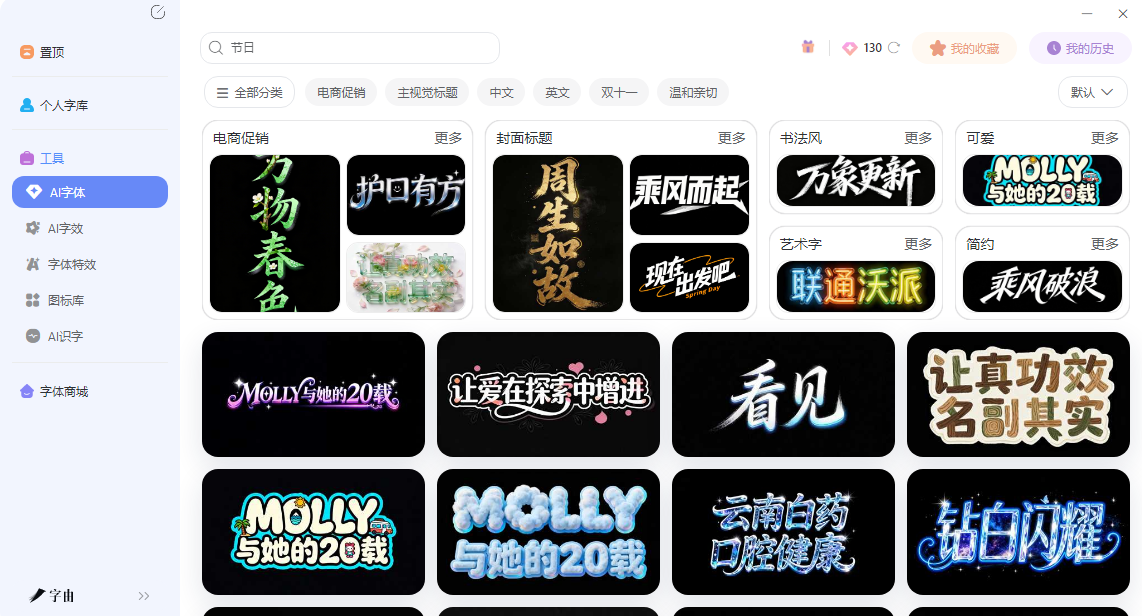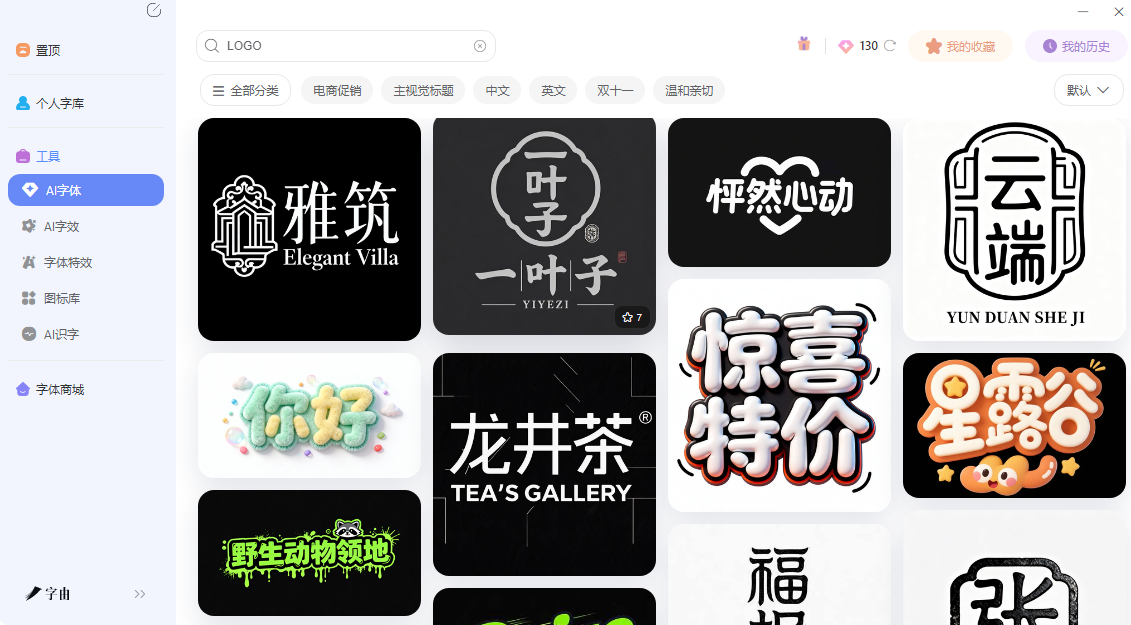
还在用普通字体?试试特殊字体生成器,一键生成
还在羡慕别人轻轻松松就能够拥有特殊字体?现在只需要通过特殊字体生成器就能够轻松实现,不需要你会PS也不需要你会设计,零基础的小白也完全可以上手,今天我就来给大家介绍5个特殊字体生成器,让你不再羡慕别人,可以自己自由地实现设计各种字体,或者不同效果的字体,心动的话先收藏本篇文章码住吧!
字由除了是字体库以外, 它的“AI 字体”功能可以看作一个强大的特殊字体生成器。打开客户端,左侧找到“工具” → “AI 字体”,你会发现里面藏着大量特殊风格的模板。和常规字体库不同,AI 字体生成的不是可编辑文字,而是直接出艺术字图片。你输入自己的文案,选一个模板,点击生成,下载 PNG 就能用。接下来我会教大家如何使用字由的AI字体来生成出特殊字体。
第二步:选择风格分类。在模板区域上方,有场景分类栏。如果你想做故障效果,可以找“科幻/科技感”分类;想做霓虹标题,找“电商促销”或“主视觉标题”分类;想做哥特字,找“文字 LOGO”或直接搜风格标签。
第三步:输入你的文案。点击任意一个模板,进入编辑界面。把默认文字删掉,输入你自己的内容。比如要做游戏封面,输入“FINAL BOSS”;要做海报,输入“限时五折”。
第四步:下载,点击生成,等待6-7秒即可生成图片。生成后,你可以直接下载透明背景的PNG图片,拖放到海报或PPT中使用都是可以的。
其中AI模板我重点推荐的有:
- 故障/Glitch:文字带错位、色差、撕裂感,适合赛博朋克风格、游戏海报。
- 霓虹发光:文字像霓虹灯管,外发光和渐变效果,适合夜间主题、酒吧海报。
- 液态/熔融:文字边缘像融化流动,带扭曲感,适合潮流品牌、实验性设计。
- 3D立体:文字带有厚度和光影层次,适合促销banner、电商标题。
- 材质纹理:文字填充金属、大理石、毛绒等材质效果。
- 哥特/暗黑:文字带尖锐装饰角,中世纪风格,适合万圣节、金属乐队主题。
AI模型预先学习了海量特定风格,比如“赛博朋克”“水墨书法”“卡通泡泡”等。当你选择一个模板并输入文字时,AI不是从零创造,而是把你的文字“装扮”成已学风格的形态,这保证了输出的高度稳定性。
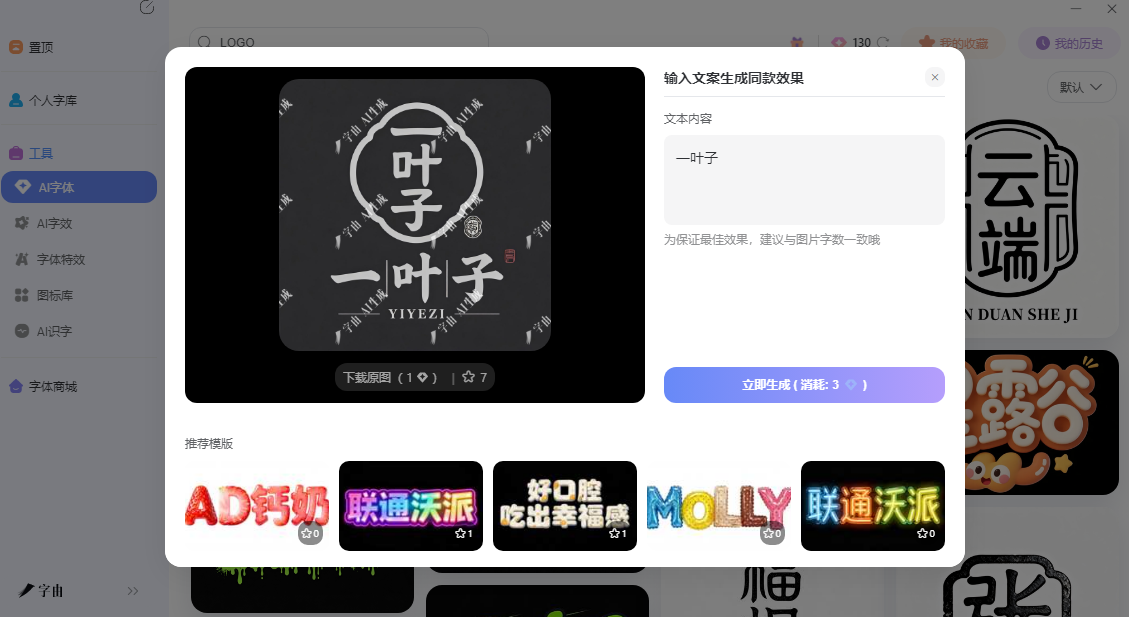
在线生成器出的是Unicode字符,复制粘贴就能用,但问题是不同设备显示可能不一样——你这边看的是花体,对方那边可能就是一个方框或者问号。而且做不了复杂的发光、3D、纹理效果。字由AI字体出的是高清图片,任何设备打开都一样,没有水印,分辨率和细节都保留得更好。缺点是生成的是图片,文字不可编辑,想改内容必须重新生成。
2、namecheap Fancy font generator
namecheap,一个老牌的域名注册服务商,它的“Visual”工具套件里包含了一个字体生成器。输入文字后,工具会自动找出对应的Unicode字符,下面会展示多种样式。提供的样式包括Gothic/Blackletter(哥特黑体)、加粗版哥特体、带圆圈字母、反色圆圈字母、等宽字体、双线字体、草书/手写体、粗体草书、带方框字母等,总共16种样式可选。
每个样式旁边都有复制按钮,点一下就能把转换后的文字复制到剪贴板,然后粘贴到任何支持Unicode的地方——社交媒体帖子、个人简介、邮件签名、游戏昵称都能用
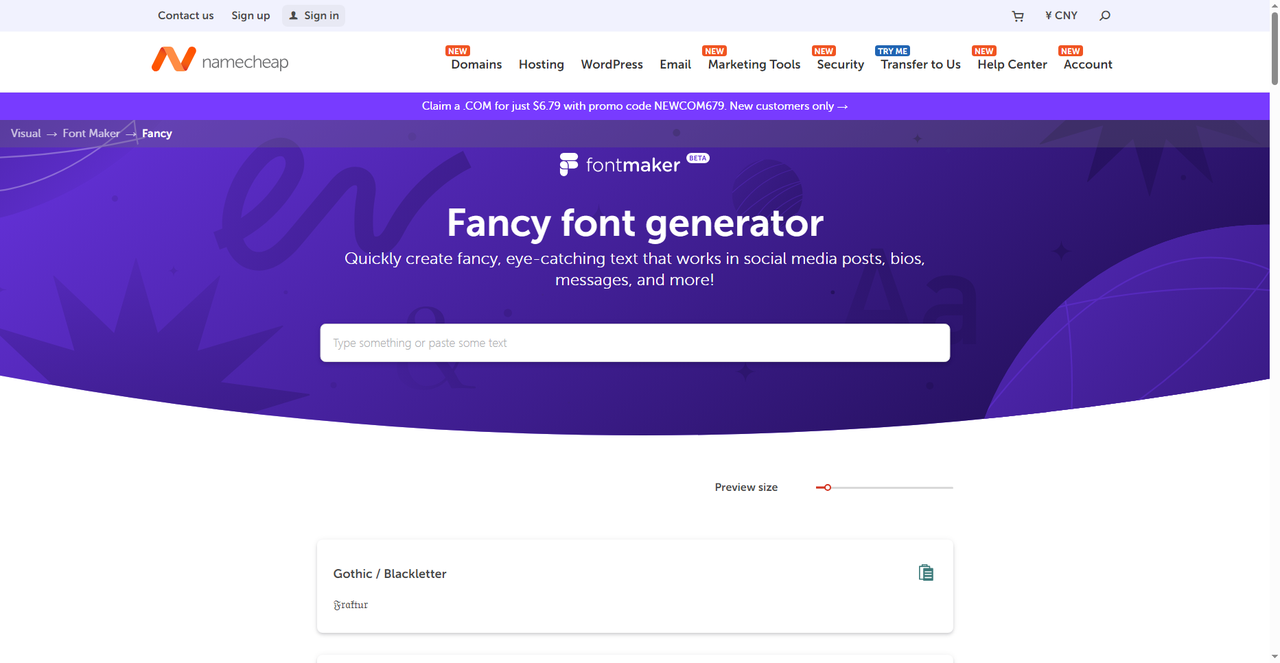
3、ontLeech Cursive Font Generator
FontLeech 是一个专门的字体资源站,提供多种草书和手写风格的转换。页面展示了多种样式:Elegant Script(优雅草书)、Bold Script(加粗草书)、Royal Style(皇室风格)、Formal Script(正式手写体)、Double Box(双框装饰)、Fraktur(德文尖角体,也是一种哥特变体)等。每个样式旁边都有“Share”和“Link”按钮,方便分享生成的文字。另外还提供Aesthetic Font、Glitch Text、Bold Text、Small Caps等其他风格生成器的入口。
这个站适合做签名、邀请函、Instagram文案,生成的也是Unicode字符,复制即用。
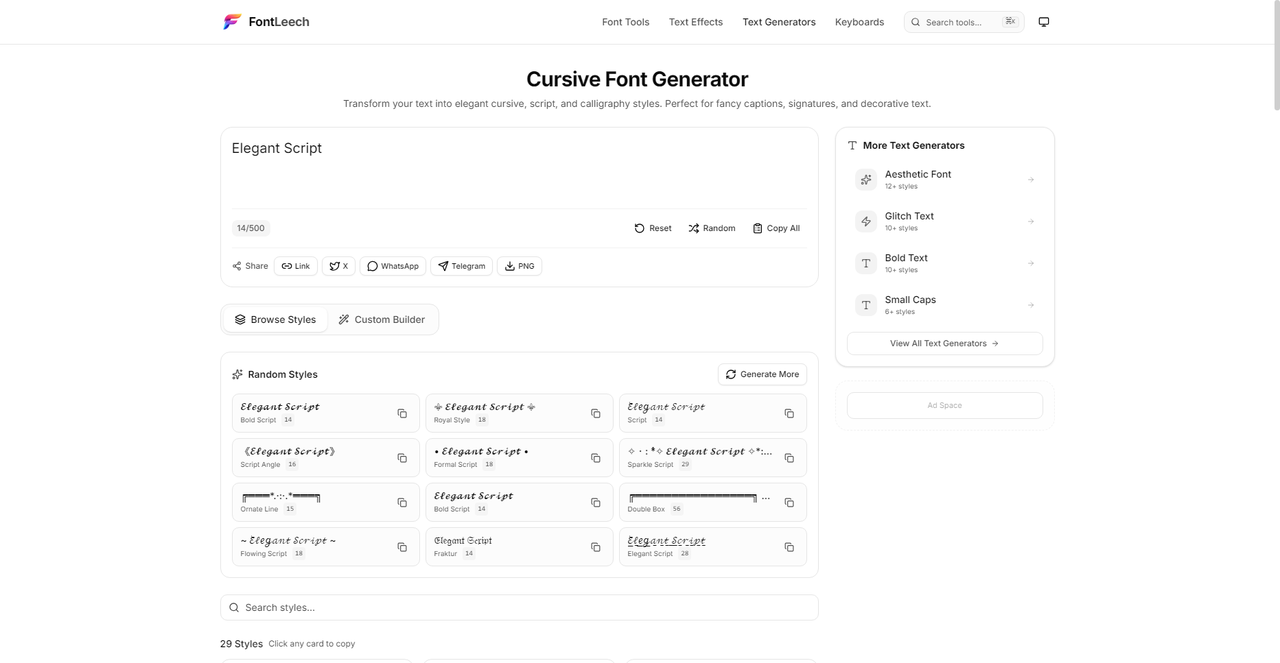
4、Retro Font Generator
Retro Font Generator 是一个复古字体生成器,主打“把你的文字带回过去”。输入文字后,网站会生成复古、蒸汽波、80/90年代风格的文字样式。这种蒸汽波美学(Vaporwave)的特点是宽间距、全角字符,带有霓虹粉蓝紫配色和模糊故障效果,灵感来自80/90年代的流行文化、科技和消费主义-。适合做怀旧主题、复古游戏视频封面、Y2K 风格内容。
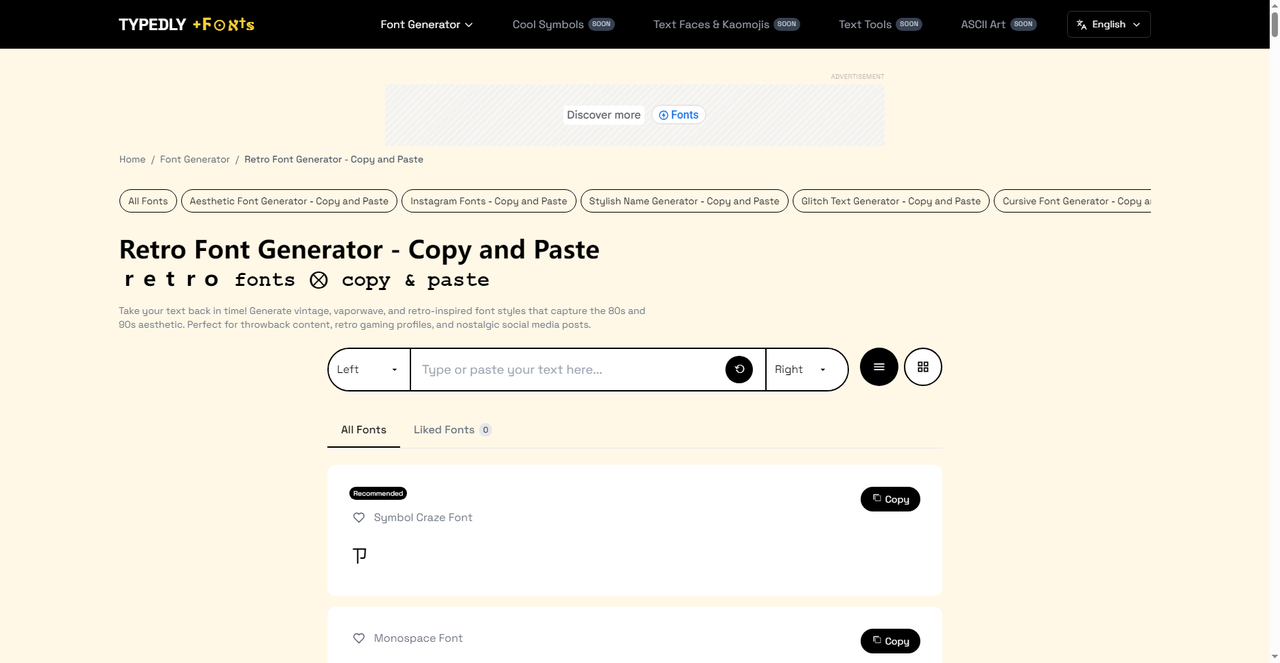
5、10TOOLS
最后一个要介绍的是一个中文界面的字体生成器,有100多种时尚字体可供选择。页面分输入区和输出区,输出区同时展示多个转换结果,每个结果下面都有复制按钮。顶部还有“安装扩展”入口,可以给浏览器加插件,方便随时调用。适合需要频繁转换文字风格的社交媒体运营者。
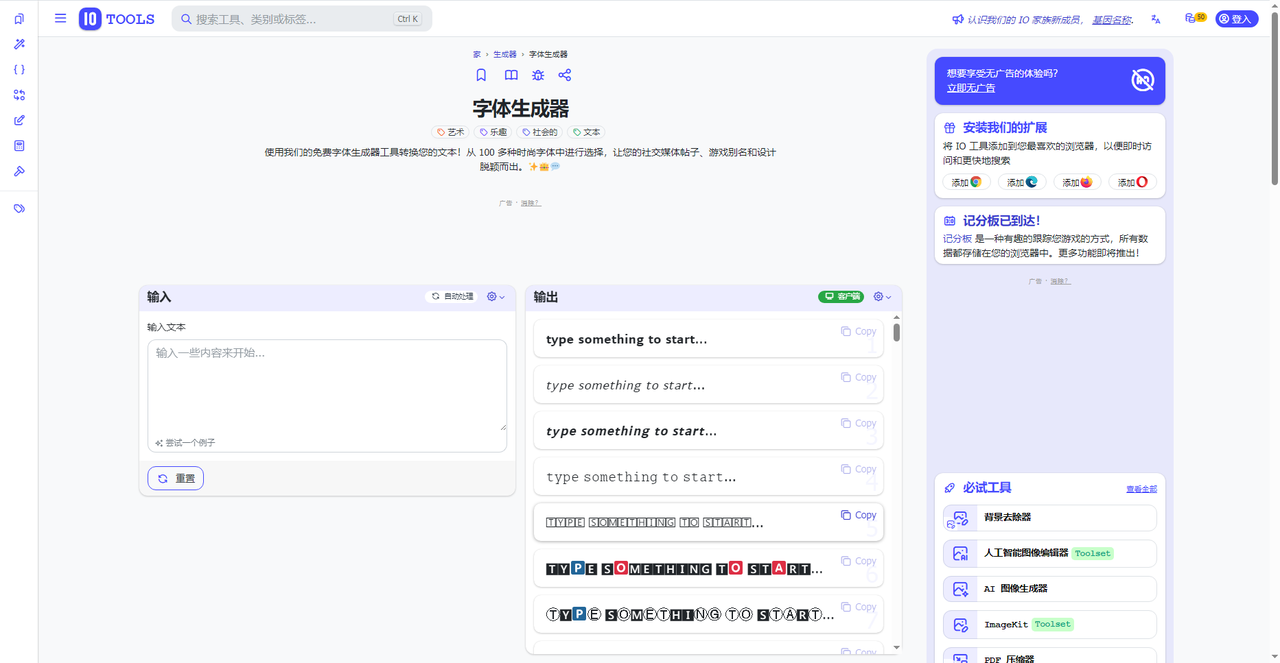
今天介绍的以上特殊字体生成器 分两类:在线Unicode生成器和AI图片生成器。如果你需要真正有设计感的特殊字体效果,去 hellofont.cn 打开“AI工具”试试。从输入文字到下载图片,三分钟搞定。如果只是想在社交平台上改个花体昵称,用后面四个在线站就够了。所以说,选特殊字体生成器之前先想清楚:你是要复制粘贴的 Unicode 字符,还是要出高清图的 AI 特效?要前者,用在线站;要后者,用字由。